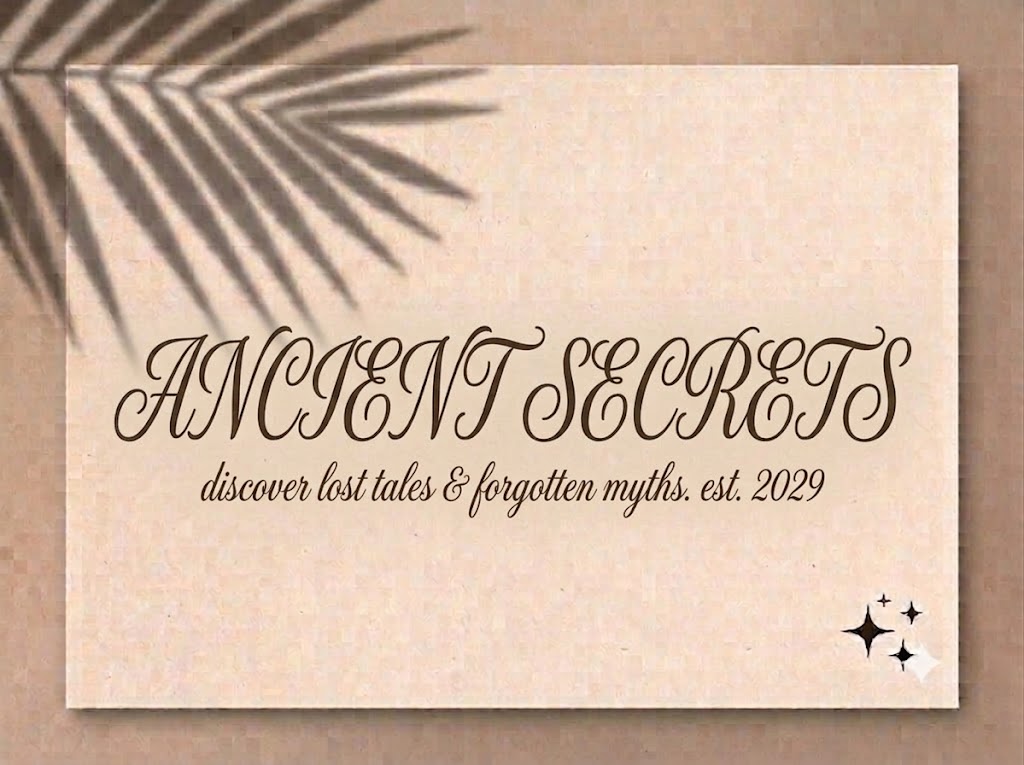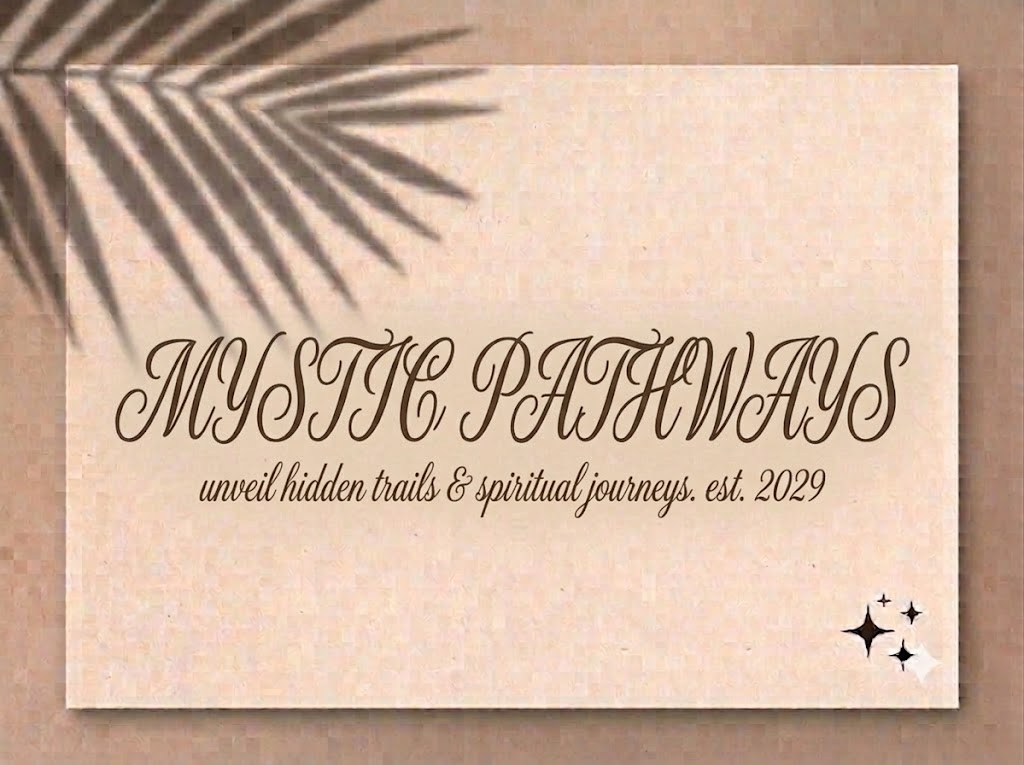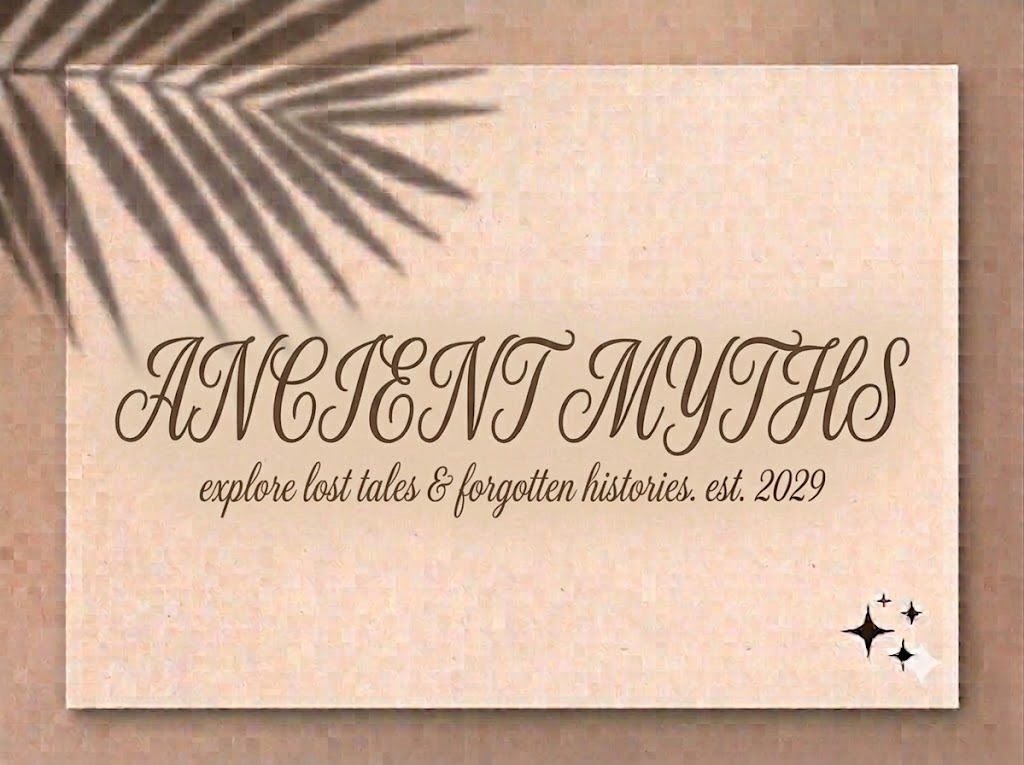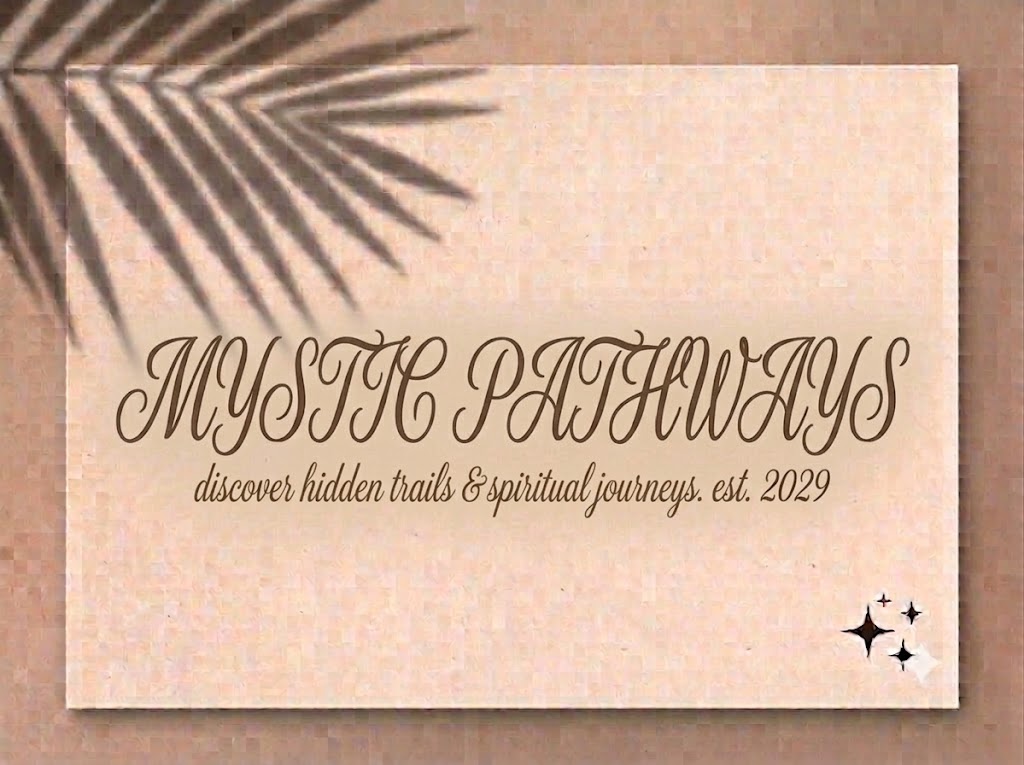
Bên cạnh những phông chữ hình khối dày dặn mang phong cách công nghiệp hiện đại, xu hướng thiết kế cao cấp và nghệ thuật vẫn luôn dành một vị trí trang trọng cho phong cách viết tay thư pháp cổ điển.
Những nét chữ uốn lượn mềm mại, uyển chuyển với độ tương phản thanh đậm rõ rệt luôn mang lại cảm giác ấm áp, lãng mạn và ngập tràn không khí lễ hội.
Nếu bạn đang tìm kiếm một bộ font chữ nghệ thuật đỉnh cao để chuẩn bị cho các dịp lễ hội cuối năm, thiết kế thiệp cưới, hay làm tiêu đề video mang phong cách sang trọng, thì font 1FTV VIP Christmas Wish chính là giải pháp không thể bỏ qua.
Giới thiệu về font 1FTV VIP Christmas Wish
Font 1FTV VIP Christmas Wish là một phông chữ hiển thị dạng viết tay thư pháp (calligraphy script) quý phái, thanh lịch và mang tính nghệ thuật cực kỳ cao.
Bộ font này được tối ưu hóa hoàn chỉnh ở phiên bản Version 1.000, đảm bảo sự đồng bộ tuyệt đối trong kết cấu cấu trúc của từng con chữ khi phối hợp tạo từ.
Nhờ những thông số kỹ thuật tối ưu này, phông chữ đảm bảo khả năng hiển thị vô cùng mượt mà, không bị vỡ nét hay răng cưa ngay cả khi bạn co giãn trên các phần mềm đồ họa chuyên nghiệp lớn.
Đặc điểm nổi bật của phong cách thiết kế Christmas Wish
Sức hút lớn nhất của font 1FTV VIP Christmas Wish đến từ sự kết hợp tài tình giữa các đường nét thanh đậm (thick and thin strokes) đầy nghệ thuật, mang đậm phong cách Copperplate cổ điển.
Khác với phiên bản nét đều (monoline), dòng font này sở hữu độ nhấn nhả lực tay rõ rệt: những nét đưa lên thanh mảnh tạo sự thanh thoát, trong khi những nét kéo xuống dày dặn tạo điểm tựa vững chãi cho con chữ.
Các chữ cái viết hoa được tạo hình như những nét vẽ phượng múa rồng bay đầy kiêu sa, tạo điểm nhấn thị giác cực kỳ mạnh mẽ cho từ mở đầu. Trong khi đó, bộ chữ cái thường sở hữu các đường nối (ligatures) uyển chuyển tạo cảm giác liền mạch như một dòng mực chảy tự nhiên.
Sự tính toán khoa học trong các vòng bo cong giúp cụm tiêu đề của bạn giữ được vẻ đẹp phóng khoáng, tự nhiên nhưng không hề bị rối mắt khi hiển thị.
Hệ thống khoảng cách chữ (kerning) và độ giãn dòng đã được căn chỉnh chuẩn xác, giúp các đường nối nét giữa chữ cái hoa và thường luôn đạt được sự liền mạch, hài hòa tuyệt đối.
Bên cạnh bộ chữ cái hoa và thường đồng bộ, phông chữ còn tích hợp đầy đủ dãy số từ 0-9 được thiết kế dáng nghiêng mềm mại cùng hệ thống các ký tự đặc biệt, dấu câu thông dụng (1234567890.:,;'"(!?)+-*/=).
Hình ảnh demo thực tế của font 1FTV VIP Christmas Wish
Để giúp bạn dễ dàng hình dung khả năng co giãn và hiển thị linh hoạt của phông chữ này trên các kích thước khác nhau, hãy cùng xem qua bảng mô phỏng từ file hệ thống image_ac3945.png:
Kích thước nhỏ (12pt – 24pt): Dù sở hữu nhiều đường uốn lượn phức tạp, các nét thanh đậm tinh tế vẫn hiển thị rõ ràng, ngay ngắn và giữ được cái hồn nghệ thuật trên màn hình di động.
Kích thước lớn (36pt – 72pt): Đây là đất diễn lý tưởng nhất để font chữ phô diễn toàn bộ sự bay bổng, kiêu sa, tạo hiệu ứng thị giác lãng mạn đỉnh cao cho các dòng headline.
Ứng dụng của font Christmas Wish trong thiết kế đồ họa và làm video
Sở hữu nét cá tính lãng mạn và cấu trúc thư pháp mềm mại, font 1FTV VIP Christmas Wish mở ra không gian ứng dụng rộng lớn cho các dự án truyền thông phân khúc cao cấp:
Thiết kế thiệp mời và thiệp chúc mừng lễ hội: Hoàn hảo để thiết kế thiệp cưới luxury, thiệp chúc mừng Giáng sinh, năm mới, Valentine hoặc thư cảm ơn gửi khách hàng mang phong cách ấm áp, trân trọng.
Làm tiêu đề video ngắn nghệ thuật (TikTok, Reels, Shorts): Rất thích hợp cho các nội dung thuộc chủ đề chữa lành, vlog đời sống nhẹ nhàng, kể chuyện tâm sự, ngâm thơ hoặc các video cinematic lãng mạn.
Ảnh thu nhỏ YouTube (Thumbnail) phong cách vintage: Đặc biệt hiệu quả với các kênh về âm nhạc acoustic, review sách, phim ảnh, chia sẻ phong cách sống tối giản hoặc nội dung lịch sử, văn hóa nghệ thuật.
Nhận diện thương hiệu và bao bì phân khúc cao cấp: Phù hợp làm logo dạng chữ ký, biểu ngữ quảng cáo hoặc nhãn mác sản phẩm cho các tiệm hoa nghệ thuật, thương hiệu mỹ phẩm, váy cưới, tiệm bánh ngọt hay các quán cà phê lãng mạn.